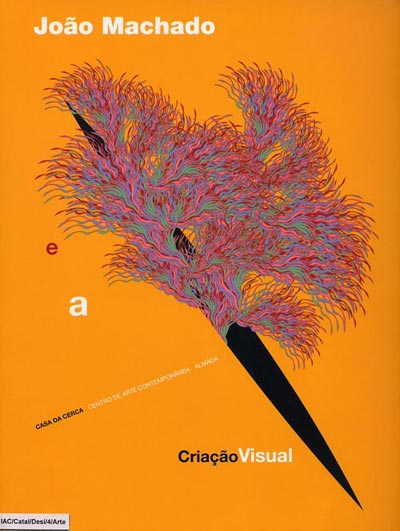
João Machado (1942- )
Designer e escultor português, vive e trabalha no Porto. Já fez mais de 400 posters, tendo ganho prémios importantes.
João Machado.
Licenciado pela Escola Superior de Belas-Artes do Porto, onde foi docente de Design gráfico entre 1976 e 1983, ano em que abandonou o ensino para se dedicar inteiramente ao design.
Em dedicação exclusiva ao graphic design, tem desenvolvido uma extensa obra de ilustrador e designer editorial, distinguindo-se pela originalidade da sua linguagem gráfica, que combina influências variadas, que vão da Pop Art à arte japonesa, através de um singular domínio das cores e da composição.
Aproximando o design gráfico das artes plásticas, João Machado tem privilegiado o cartaz, mas também tem dado atenção aos selos do correio e ao design corporativo.
João Machado tem exibido a sua obra em algumas das mais importantes galerias e museus do mundo e tem sido objecto dos mais diversos prémios e distinções nacionais e internacionais como ilustrador e designer – destacando-se o "Prémio de Excelência Icograda 1999" e o "Aziago International Award 2005".
Nasceu em Coimbra em 1942. Formou-se em Escultura na Escola Superior de Belas Artes do Porto. Depois orientou-se para o desenho e criação gráfica.
Duas obras publicadas no Porto pelas edições ASA ( em 1982 e 1988 ) apresentam algumas das suas realizações e demonstram a eficácia de uma linguagem gráfica que utiliza símbolos e elementos da Pop Art e conjuga o texto e a imagem numa síntese poética da realidade.
João Machado e a Criação visual: Almada Editora: Casa da Cerca: 2001
xposições individuais
• 1982 Museu Nacional de Soares dos Reis, Porto
• Sociedade Nacional de Belas Artes, Lisboa
• 1985 Richmond Art Gallery, Montreal, Canadá
• 1986 Art Poster Gallery, Lambsheim, Alemanha
• Museu Nacional de Soares dos Reis, Porto
• 1987 Annecy/Bonlieu - Centre d’Action Culturelle, França
• 1989 Lincoln Center, Colorado, EUA
• 1991 Dias da Cultura Portuguesa, Frankfurt, Alemanha
• 1996 Galeria de la Casa del Poeta, Cidade do México, México
• 1997 DDD Galery, Osaka, Japão
• Museu Nacional de Belas Artes, Rio de Janeiro, Brasil
• Memorial da Cidade, Curitiba, Brasil
• Museu Brasileiro da Escultura, S. Paulo, Brasil
• 1998 Casa Garden, Macau
• 2001 ESAD, Escuela Superior de Administración e Dirección de Empresas, Barcelona/2001 Casa da Cerca, Almada, Portugal Pécsi Galéria, Pécs, Hungria
• 2002 Dansk Plakatmuseum, Arhus
Prémios
• 1º Prémio Nacional Gulbenkian para a melhor Ilustração de Livros para a Infância, Lisboa, Portugal
• 1º Prémio Grafiporto (Ilustração) 1985
• 1º Prémio Nacional de Design, Portugal 1989 Prémio Especial da “Die Erste Internationale Litfass Kunst Biennale”, Munique, Alemanha
• Medalha de Bronze da Bienal do Livro de Leipzig, Alemanha 1996
• Menção honrosa, “Computer Art Bienal”, Rzeszow, Polónia 1997
• 1º Prémio Mikulás Galanda, Bienal do livro de Martin, Eslováquia
• 1º Prémio “First International Competition for Fair Poster”, Bulgária 1996
• 1º Prémio para Logo Film Commission, Association of film Commissioners International Denver, EUA 1999
• 1º Prémio Best of Show, European Design Annual, Grã-Bretanha
• Prémio Zgraf 8 Icograda Excellence, Croácia 2004
• Medalha de Bronze, 4th International Triennal of Stage Poster, Bulgária. 2005
• Prémio “Asiago Inernational Award 2005”, para Emissão Filatelia “Europa 2004 – Turismo”, Asiago.